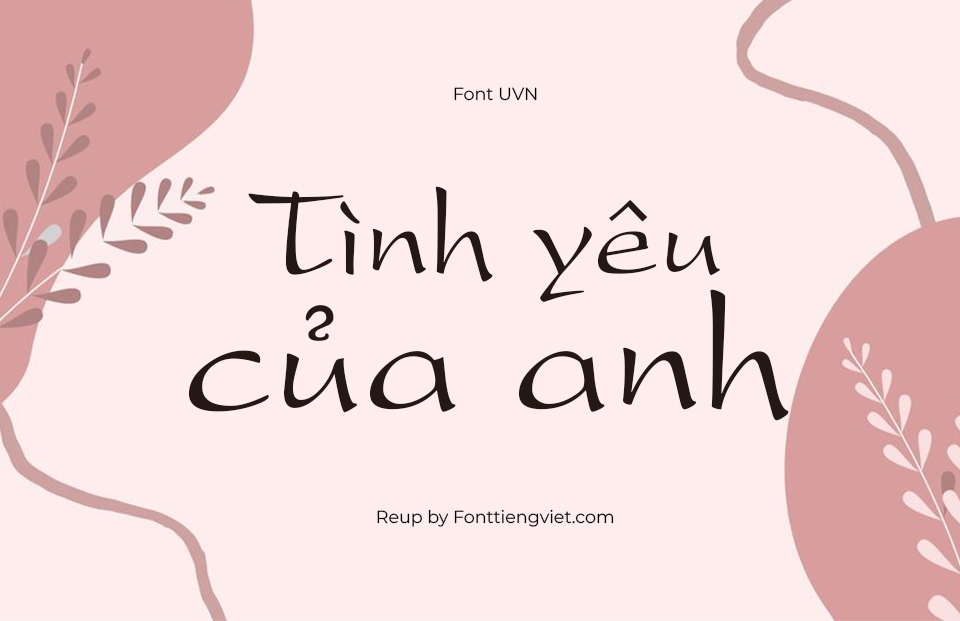
Tải Font Việt Hóa UVn Bay Buom Miễn Phí Đẹp Nhất Cho Thiết Kế
Trong thế giới thiết kế đồ họa, việc lựa chọn một bộ Font Chữ phù hợp đóng vai trò quyết định đến tính thẩm mỹ của sản phẩm. Font Việt Hóa UVn Bay Buom là một trong những lựa chọn hàng đầu dành cho những ai yêu thích phong cách nghệ thuật, bay bổng và đầy sáng tạo. Được tối ưu hóa hoàn toàn cho bảng mã Unicode, bộ phông này giúp người dùng dễ dàng soạn thảo các văn bản tiếng Việt mà không lo gặp lỗi hiển thị hay mất dấu. Đây là công cụ đắc lực giúp hiện thực hóa những ý tưởng thiết kế độc đáo từ các trang bìa sách đến những tấm thiệp mời sang trọng.
Đặc điểm nổi bật của Font Việt Hóa UVn Bay Buom
Phong cách thiết kế nghệ thuật
Font Việt Hóa UVn Bay Buom sở hữu những đường nét thanh mảnh, uốn lượn mềm mại như cánh bướm đang bay. Kiểu dáng của phông chữ này mang đậm nét thủ công, tạo cảm giác gần gũi nhưng không kém phần tinh tế. Với sự kết hợp giữa các nét dày và mỏng đan xen, bộ font tạo nên một nhịp điệu thị giác ấn tượng, giúp các dòng tiêu đề trở nên nổi bật và thu hút ánh nhìn ngay từ lần đầu tiên. Đây là sự lựa chọn tuyệt vời cho các dự án đòi hỏi sự nữ tính, nhẹ nhàng và giàu cảm xúc.
Tính ứng dụng linh hoạt trong đời sống
Bộ phông này được ứng dụng rộng rãi trong nhiều lĩnh vực khác nhau. Các giáo viên và học sinh thường sử dụng để trang trí bảng tin, làm báo tường hoặc thiết kế các slide bài giảng sinh động. Trong lĩnh vực in ấn, nó thường xuất hiện trên bao bì mỹ phẩm, thiệp cưới, và các poster quảng cáo sự kiện văn hóa. Nhờ tính tương thích cao với các phần mềm đồ họa chuyên nghiệp như Photoshop, Illustrator, người dùng có thể tự do sáng tạo và biến hóa bộ chữ này theo phong cách riêng của mình.